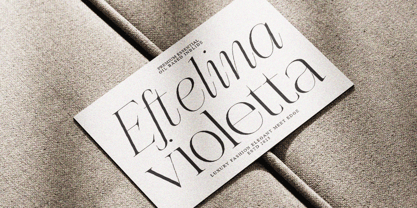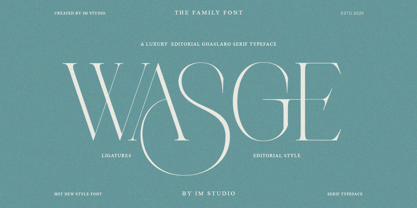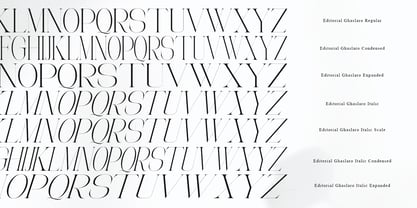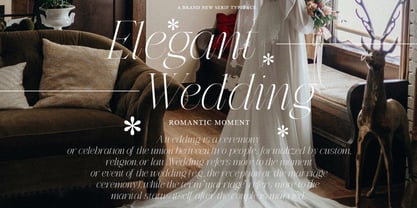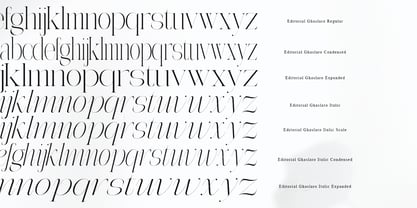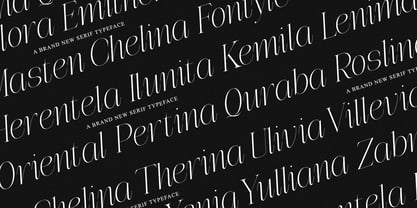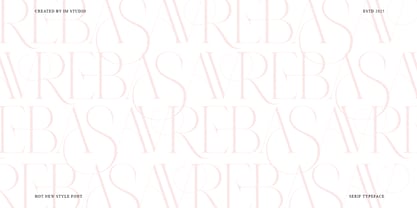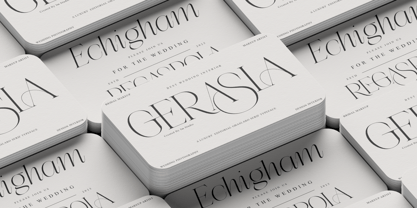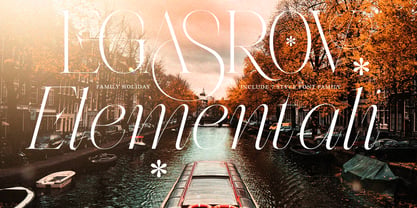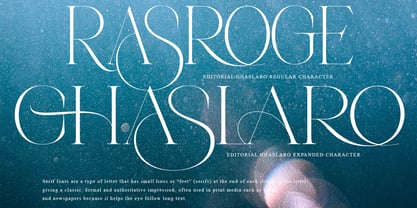
Editorial Ghaslaro
Die Schriftfamilie Editorial Ghaslaro wurde von Ikhsan Maulana entworfen und von IM Studio veröffentlicht. Editorial Ghaslaro enthält 7 Stile und Familienpaketoptionen. Mehr über diese Familie
Editorial Ghaslaro | 7 Font Styles – Modern Serif Font Family Elevate your designs with Editorial Ghaslaro, the ultimate modern display serif typeface, luxury serif font, and premium display font serving timeless elegance meets next-level edge. Subtle contrasts and fluid curves drop that high-end typography flex—perfect serif font family for projects screaming sophisticated fonts, elegant serif, and scroll-stopping luxury typography. Ultra-versatile display serif font for branding fonts, logo serif fonts, runway editorial font family, magazine typography fonts, packaging that pops, and any creative hustle craving that premium serif typeface punch. Unlock this modern serif font family, high-end display serif, and creative market typography that's redefining luxury editorial fonts—grab it now and level up your premium font collection!